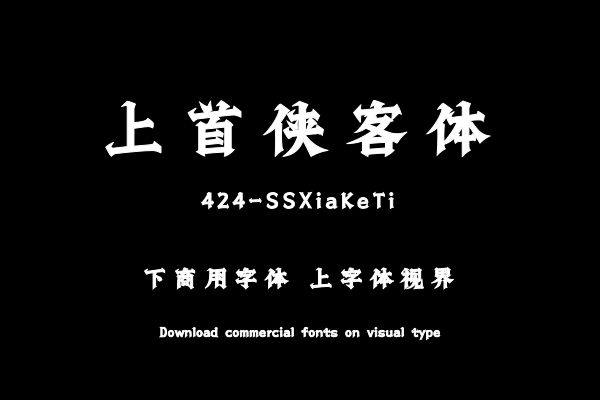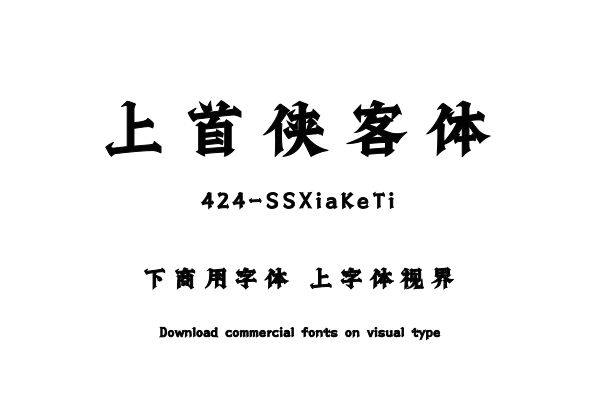
上首侠客体,简体中文约6763字。字体整体四方稳当,衔接之处优雅得当,竖笔笔锋干净笔直。整体字形凌厉肃杀,仿佛令人置身于快意恩仇的江湖中。适用于搭配标志、广告标......购买须知:“下载服务费”与“字体VIP”所获得字体 仅用于个人非商用, 商用请联系付费授权。本字体为电脑用字,手机没有root权限不支持直接手机换字(手机如何root,请自行百度搜索教程)。购买前请先 了解清楚后再付款 ,字体为虚拟产品无法回收 一旦购买不支持退款。